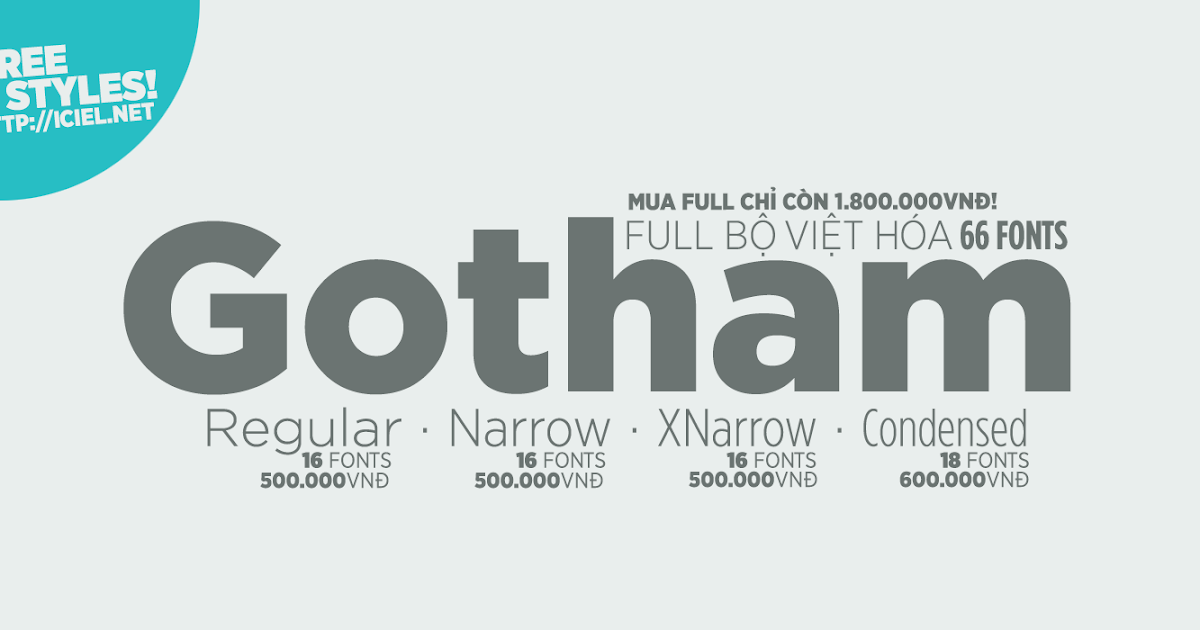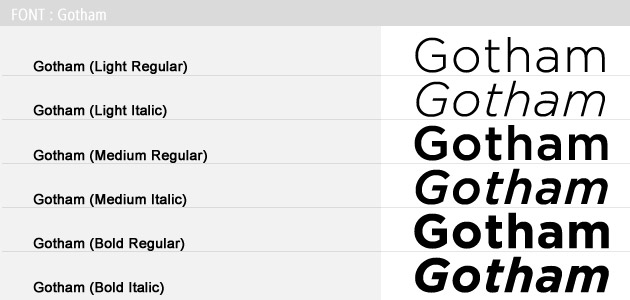
3 Google Fonts Похожие на Gotham
Gotham — это шрифт без засечек, созданный в 2000 году Тобиасом Фрер-Джонсом. Шрифт стал популярным, так как он использовался в президентской кампании Обамы.
Известен большой x-высотой и апертурой. Этот шрифт отлично подходит для заголовков и заголовков. На рынке есть много альтернатив, некоторые из которых бесплатны. Однако, если вам нужен сам шрифт, вам придется купить его прямо у производителя.
К счастью, мне удалось найти несколько похожих шрифтов в Google Fonts. Они не точны, но очень близки!
Какие шрифты Google похожи на Gotham?
Шрифты, которые я нашел наиболее похожими на Gotham:
- Montserrat
- Open Sans
- Lato
Montserrat
Montserrat — это шрифт без засечек, вдохновленный старыми плакатами и вывесками в старом районе Монтсеррат.
Этот шрифт представляет собой красивую городскую типографику, появившуюся в первой половине двадцатого века.
Отличный шрифт как для заголовков, так и для основного текста абзаца. Этот шрифт поставляется с полным набором начертаний шрифта, чтобы соответствовать любой ситуации, в которой вы нуждаетесь.
Этот шрифт наиболее похож. В строчной форме он почти идентичен.
При ближайшем рассмотрении есть несколько незначительных отличий. Например, в «Монтсеррат против Готэма» буква «м» немного шире. В целом, это была бы отличная замена шрифта для него.
Убедитесь сами!
Открытый шрифт без шрифта
Open Sans — это шрифт без засечек, представляющий нейтральный и дружелюбный дизайн. В основном его следует использовать для основного текста абзаца, но его можно использовать и для заголовков.
Open Sans и Gotham тоже очень похожи друг на друга. Письма легко читаются, дружелюбны и доступны. Они оба имеют уникальные короткие буквы «j» и «f».
Основное отличие в букве «g».
Буква «g» в Open Sans представляет собой две петли друг над другом. Это было бы полной раздачей, что это не Готэм. Однако, если вам нужен похожий внешний вид, отличной альтернативой будет Open Sans.
Вот несколько примеров.
Lato
Lato — отличный, легко читаемый шрифт без засечек. Он имеет классические пропорции, которые отлично подходят для заголовков в верхнем регистре.
Многие из его букв имеют символы, похожие на символы Готэма, с некоторыми отличиями. Они имеют схожий внешний вид, но основное различие заключается в буквах «g» и «y». Буква «g» в открытом гротеске представляет собой две полные петли друг над другом, а «y» не имеет хвоста, падающего на нижний штрих.
Вот почему это будет мой третий выбор. Это будет отличная альтернатива, если ни Montserrat, ни Open Sans не работают.
Взгляните.
Gotham, к счастью, имеет несколько действительно хороших альтернатив Google Font. Монтсеррат будет вашим лучшим выбором.
Однако, если это вам не подходит, Lato и Open Sans — отличные альтернативы.
Возможно, очень немногие люди знают, что шрифт Gotham является одним из самых популярных шрифтов в индустрии шрифтов, и многие дизайнеры хотели бы использовать этот шрифт в своих проектах. Это не потому, что он популярен, но есть много причин для использования этого стильного шрифта, которые мы собираемся здесь рассмотреть.
Прежде всего, давайте посмотрим на фон этого шрифта. Он был разработан профессиональным американским дизайнером Тобиасом Фрере Джонсом в 2000 году и после его выпуска. Он привлек внимание многих дизайнеров со всего мира.
После использования во многих кампаниях, особенно в кампании Обамы, этот шрифт достиг своего пика, и с тех пор все без ума от использования этого шрифта в своих проектах.
Основной причиной, по которой этот шрифт нравится большинству людей, является его уникальность и креативность. Дизайнеры просто хотели бы использовать его креативный дизайн в своих проектах и сделать их более профессиональными и удобными для пользователя.
Мы знаем, что каждый хочет сделать свой дизайн более красивым, профессиональным и креативным, и если вы один из них, мы рекомендуем вам использовать шрифт Gotham Pro в своих проектах.
Если вы посмотрите на дизайн шрифта Gotham Black, вы увидите, что он имеет очень разные вариации, например, человек, который хочет использовать закругленный шрифт, может легко использовать этот шрифт.
Вы можете проверить этот красивый и стильный шрифт. Поскольку это один из самых красивых шрифтов, таких как шрифт Supreme, и разные веб-дизайнеры хотели бы использовать его в своих дизайнерских проектах. Поэтому мы не думаем, что вы тоже хотите пропустить этот шрифт, потому что его также можно считать альтернативным шрифтом.